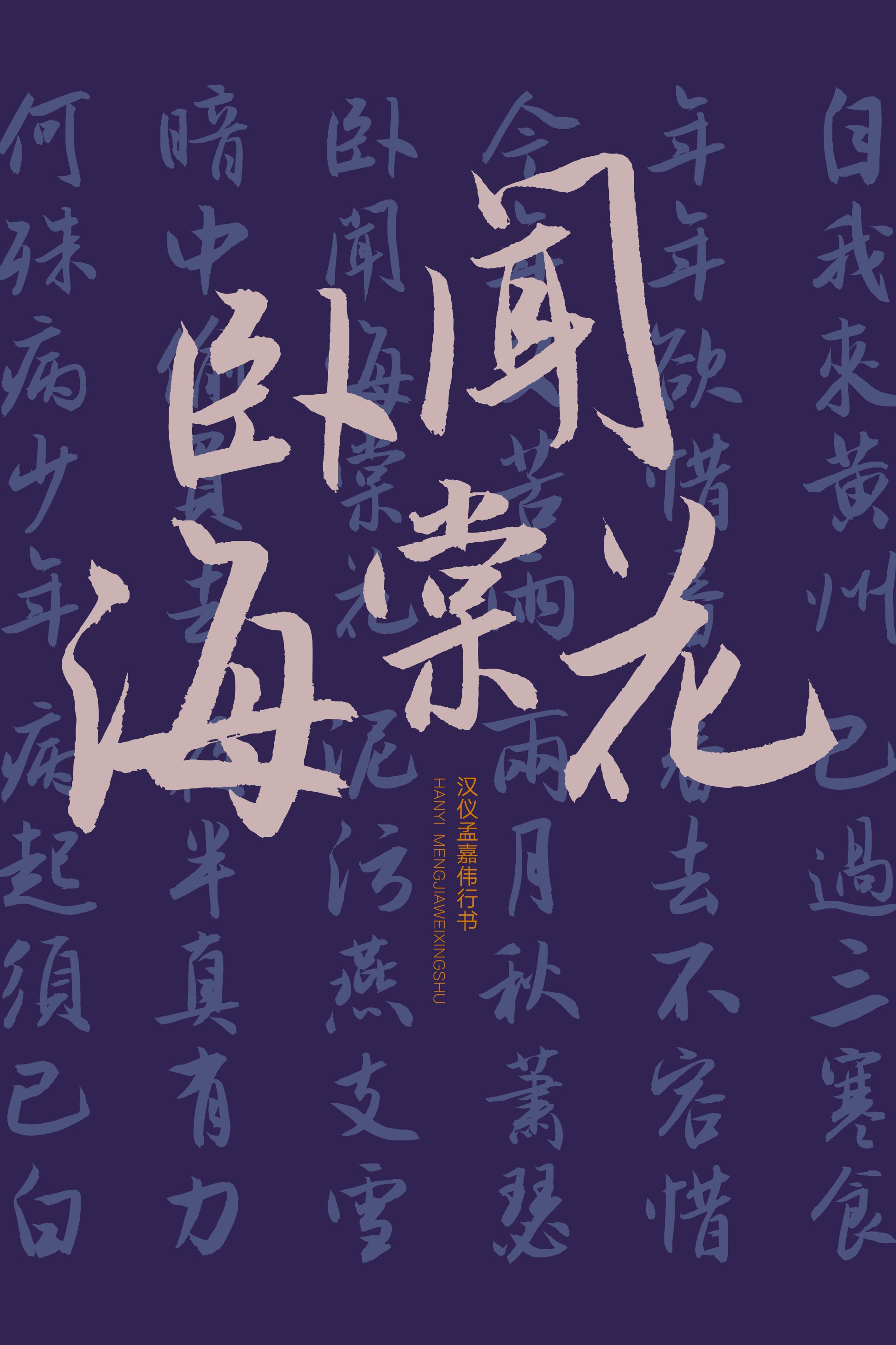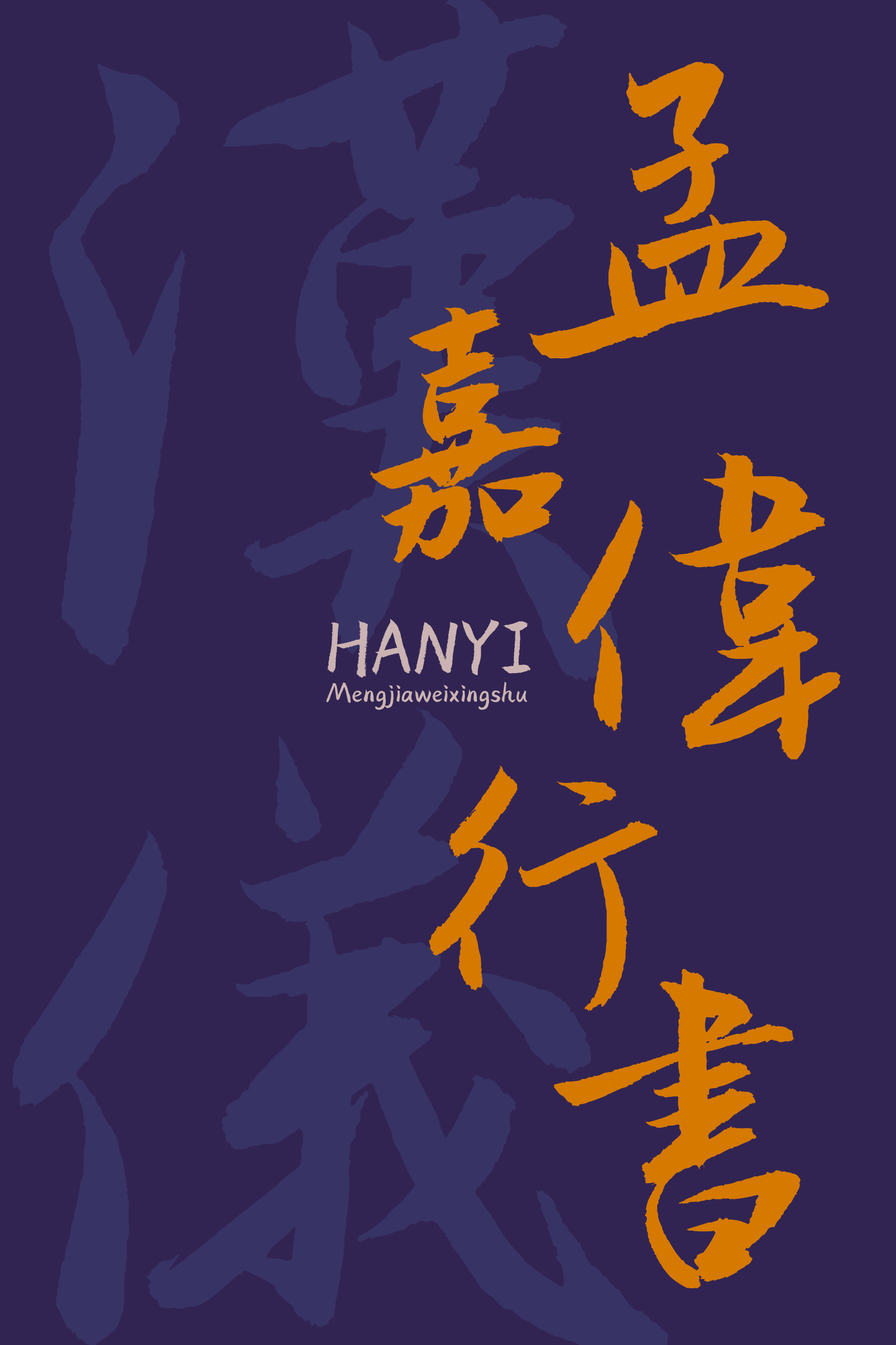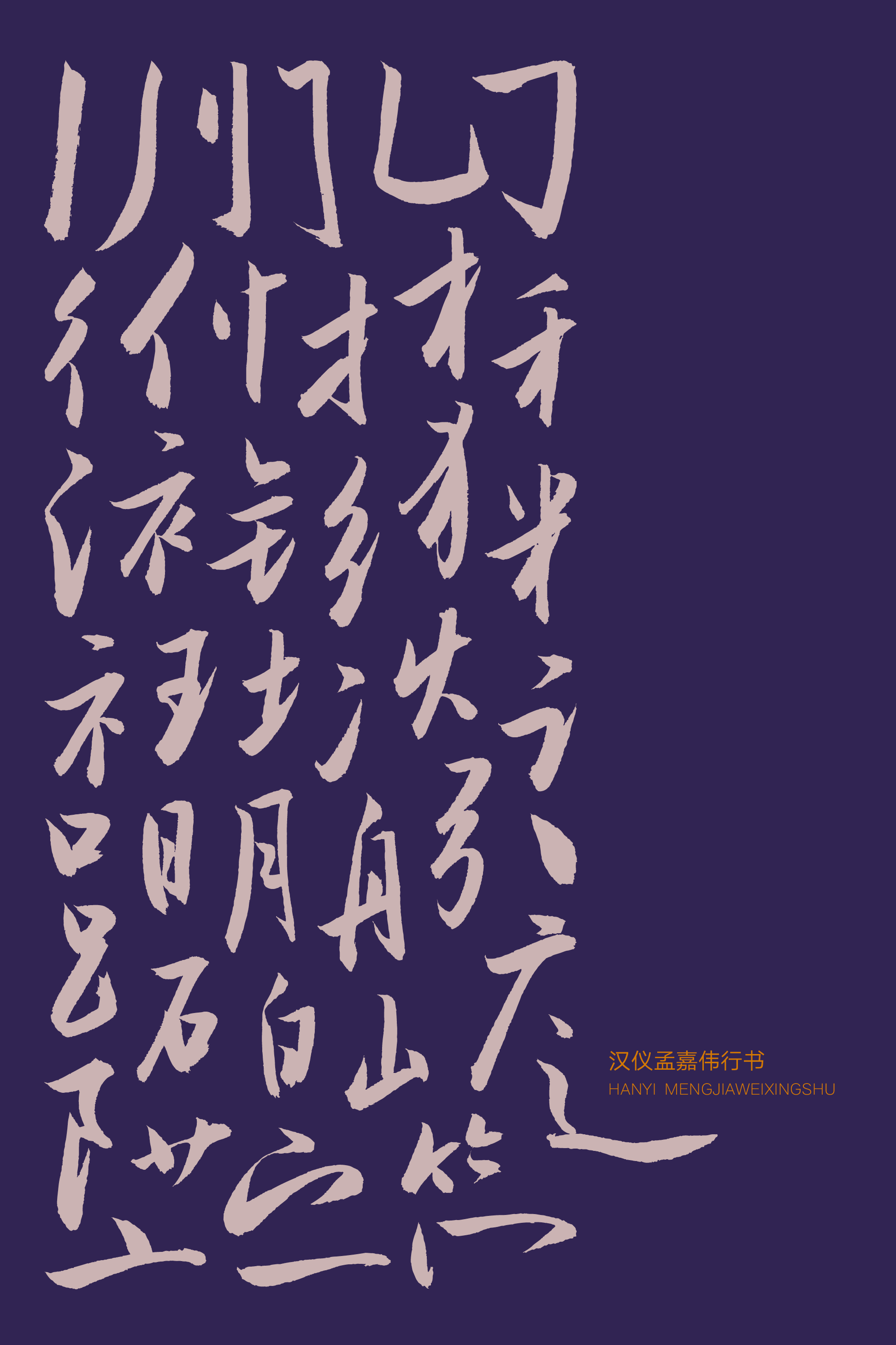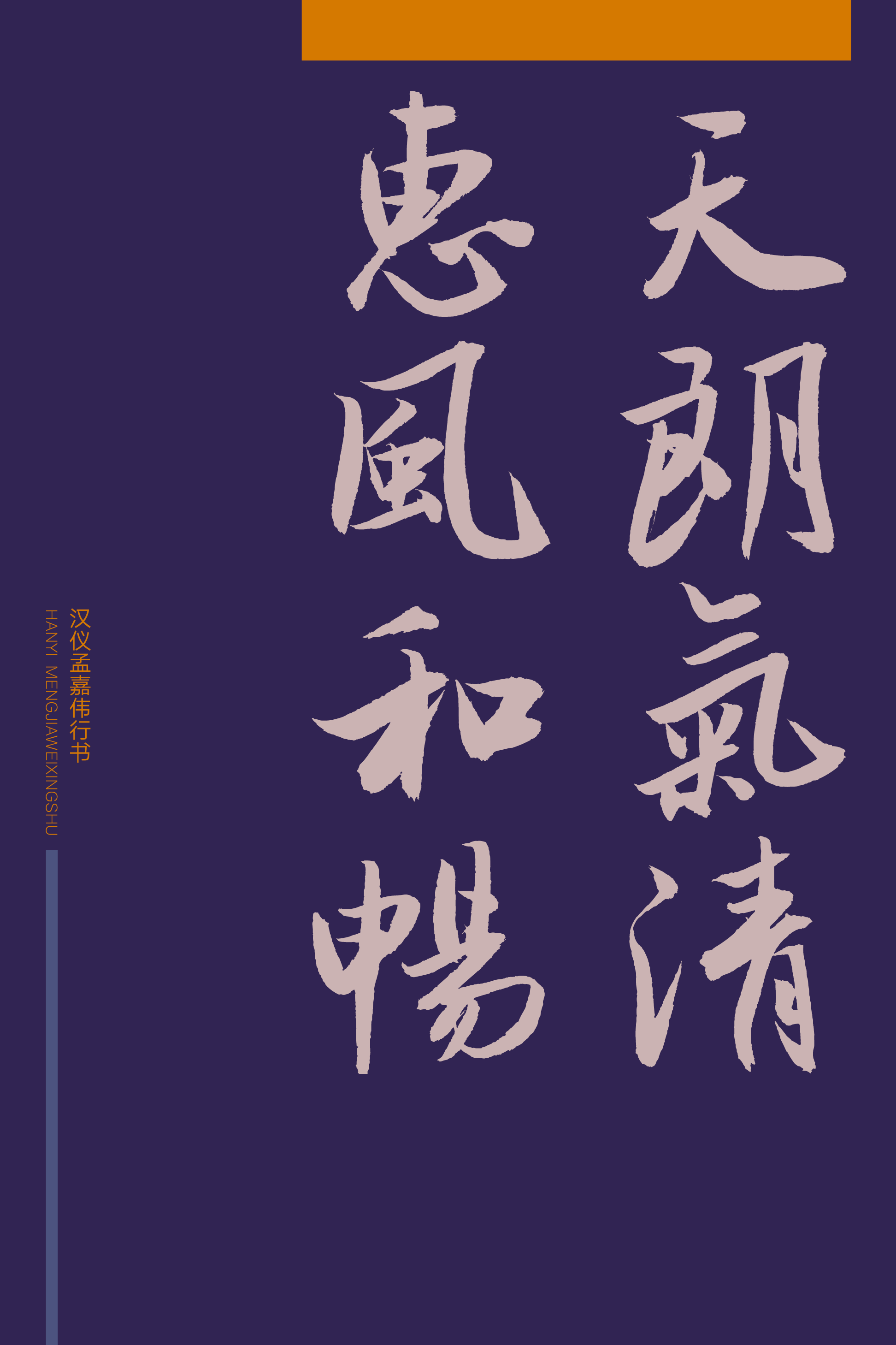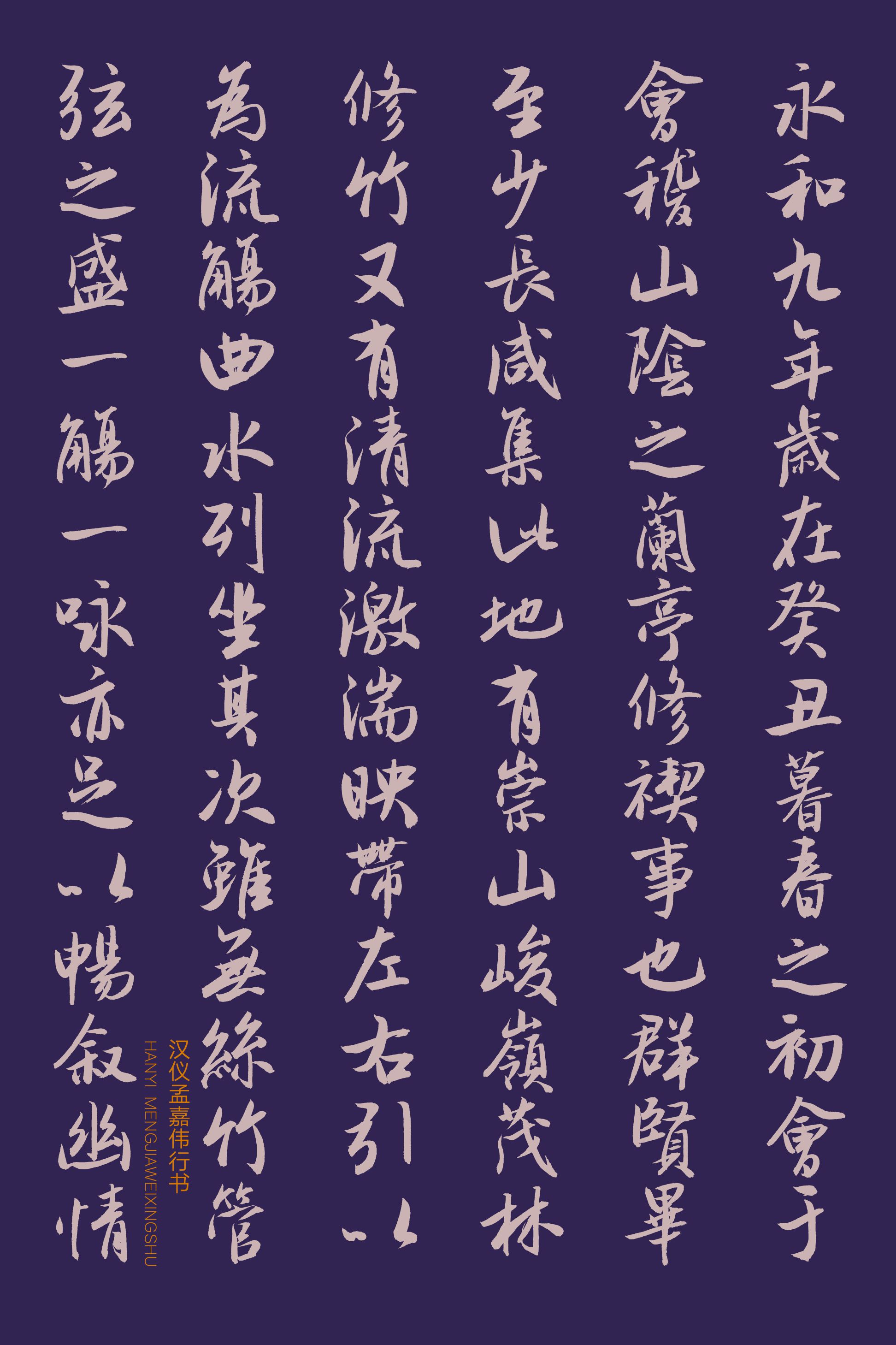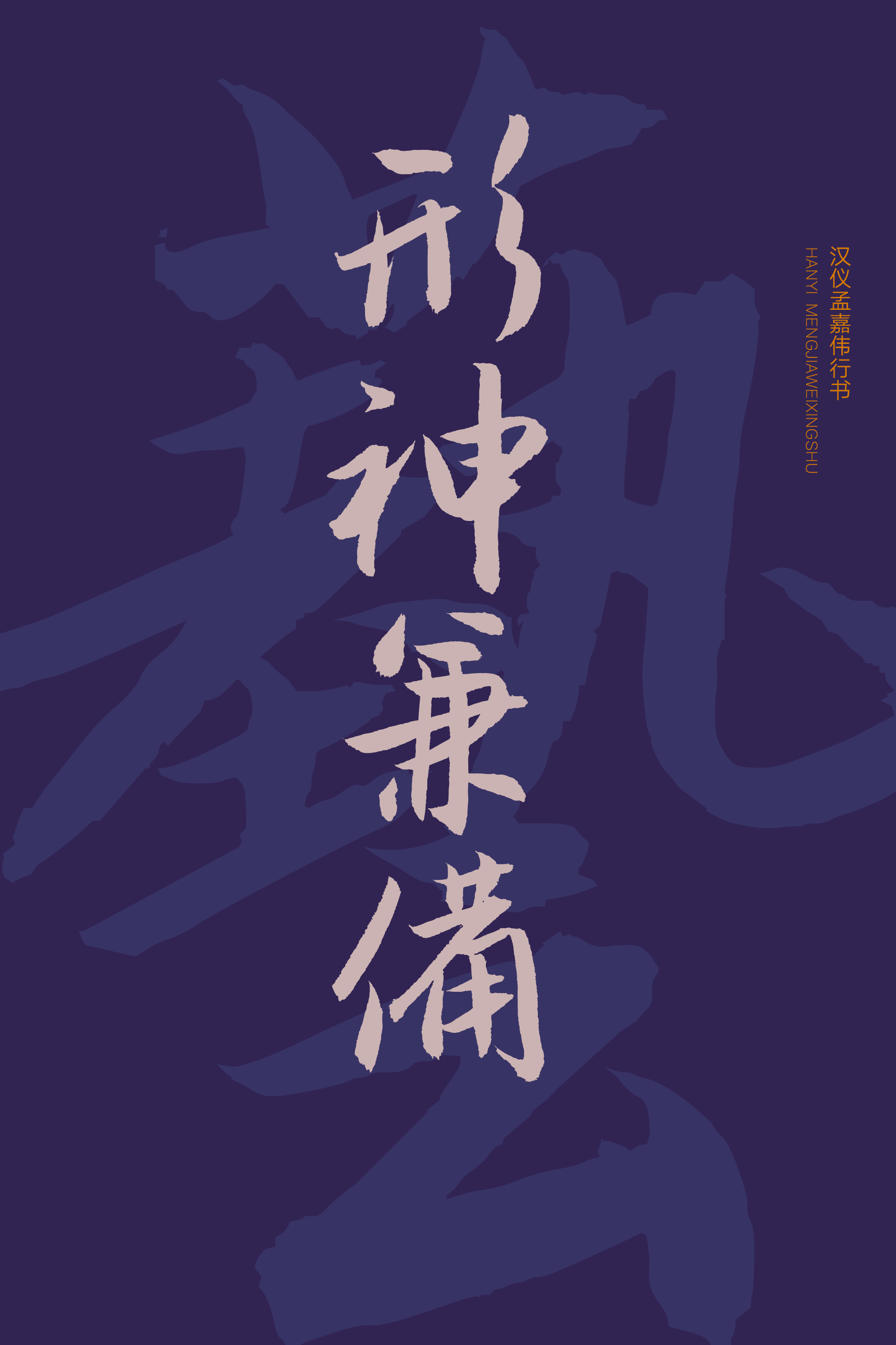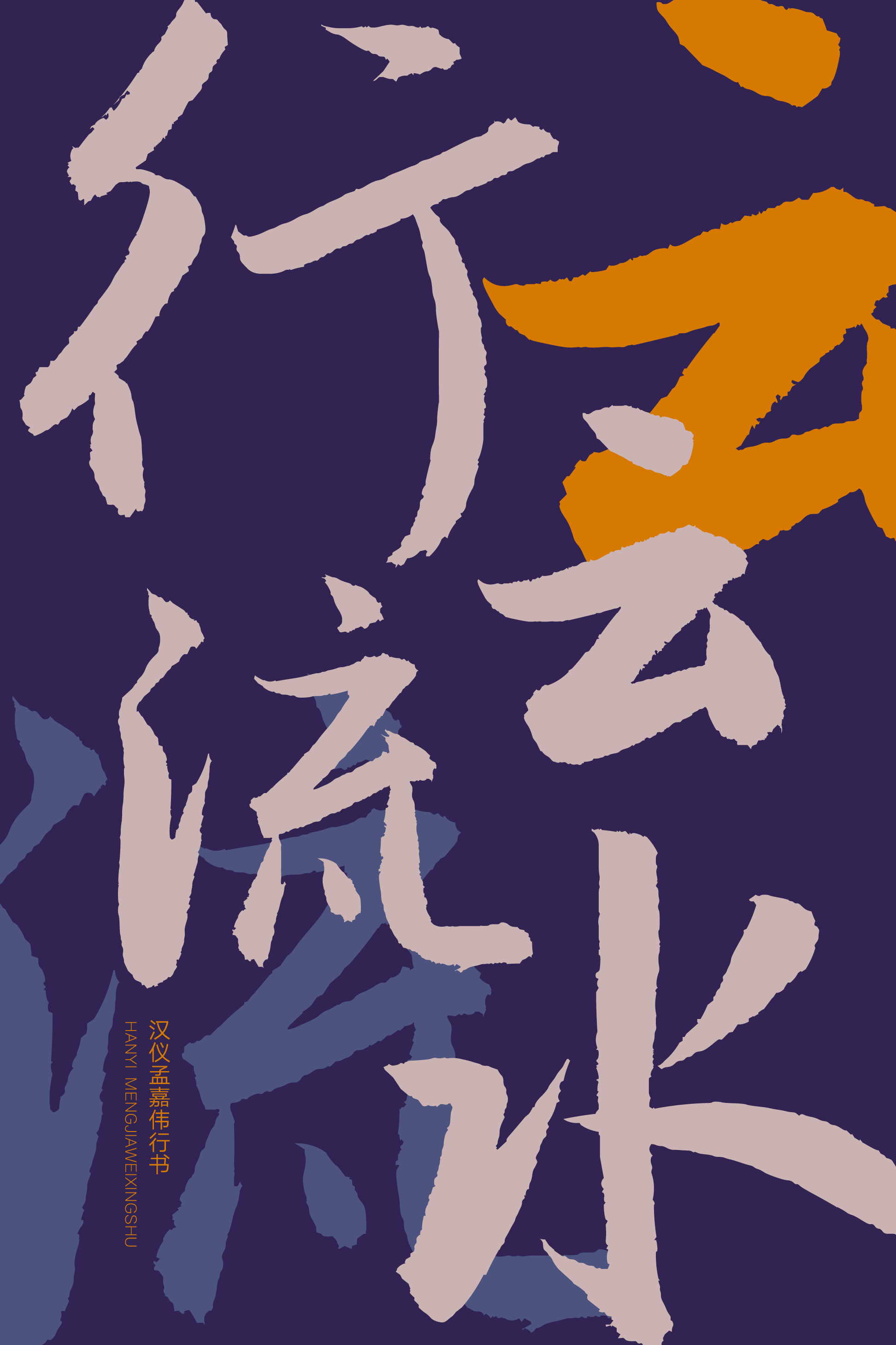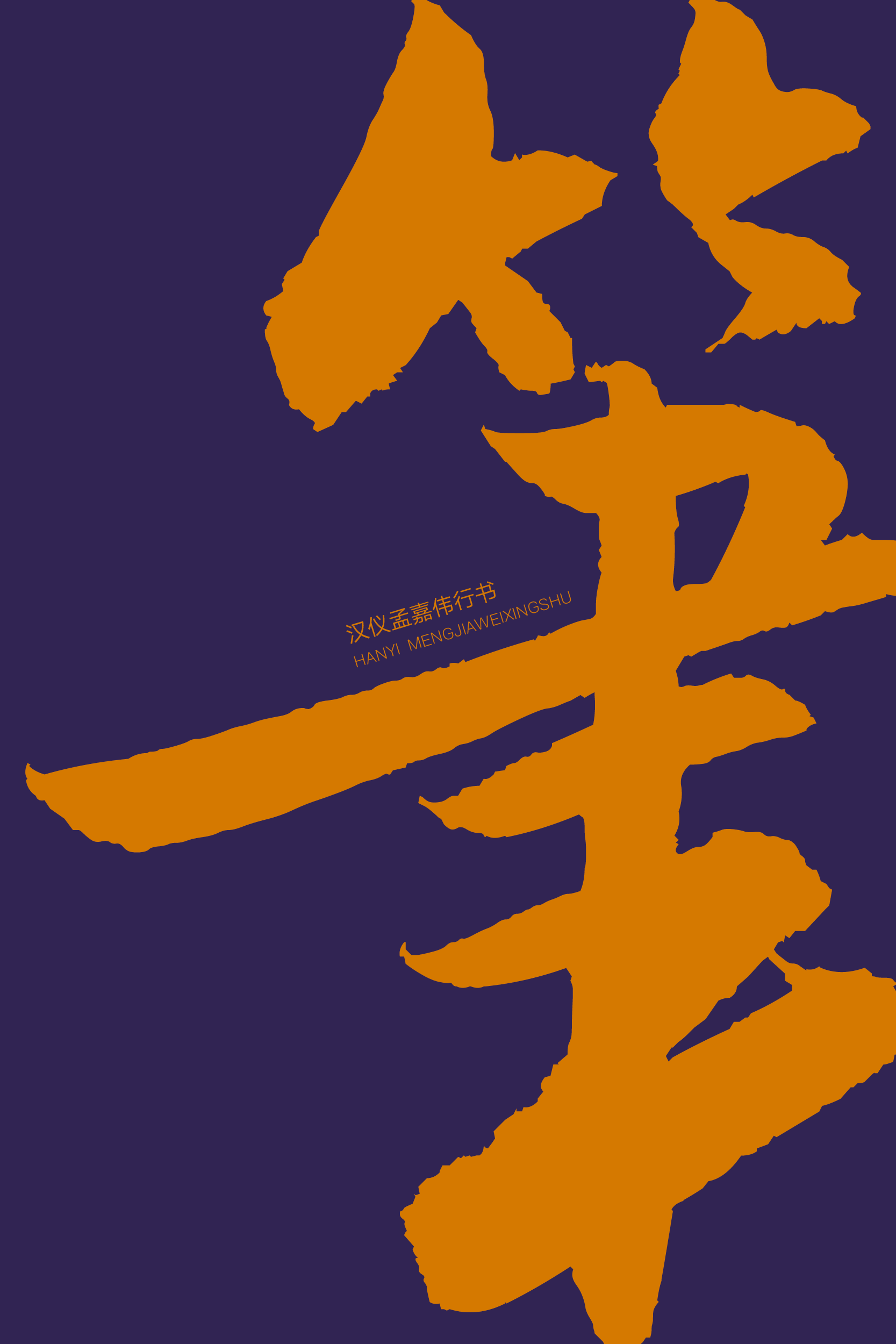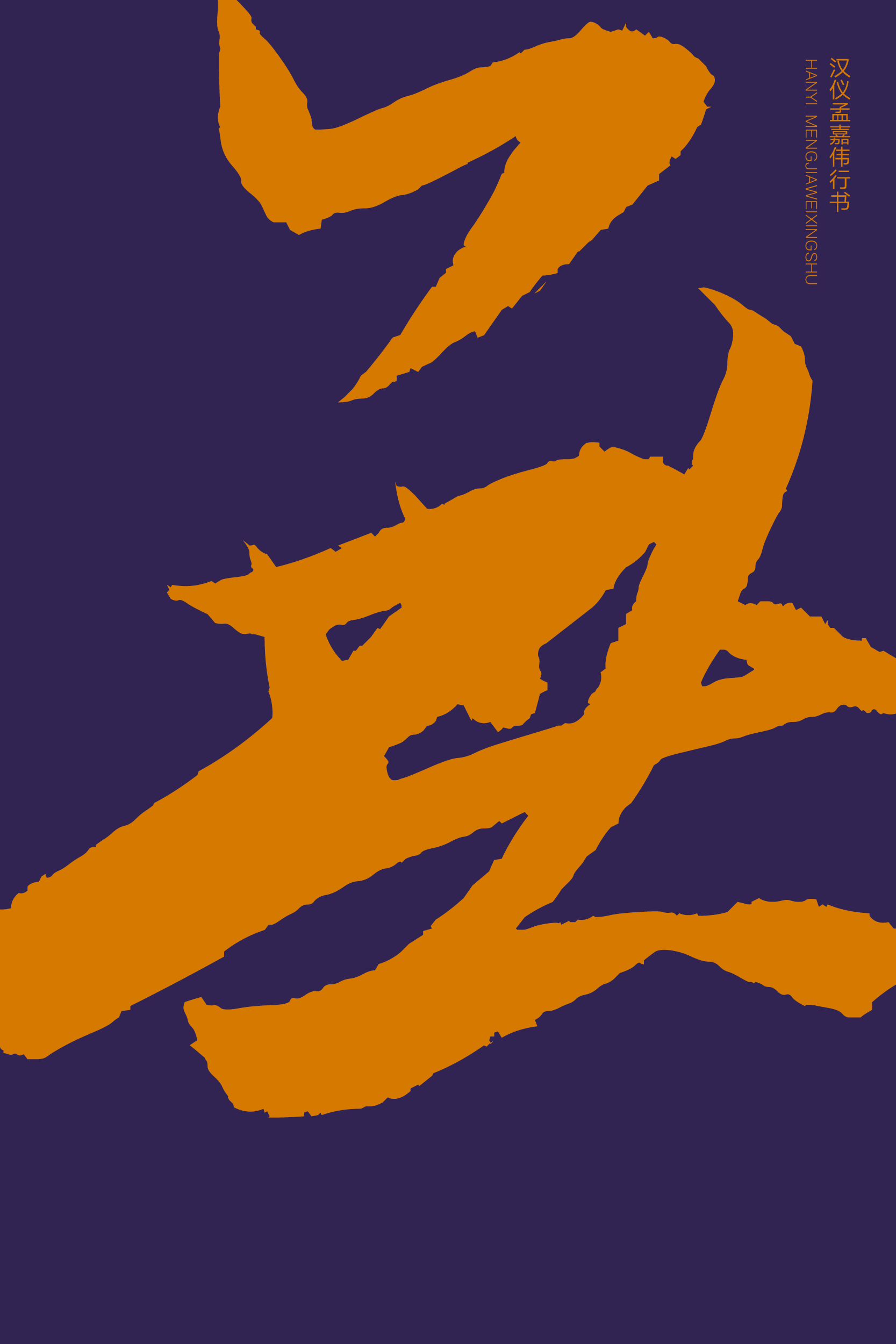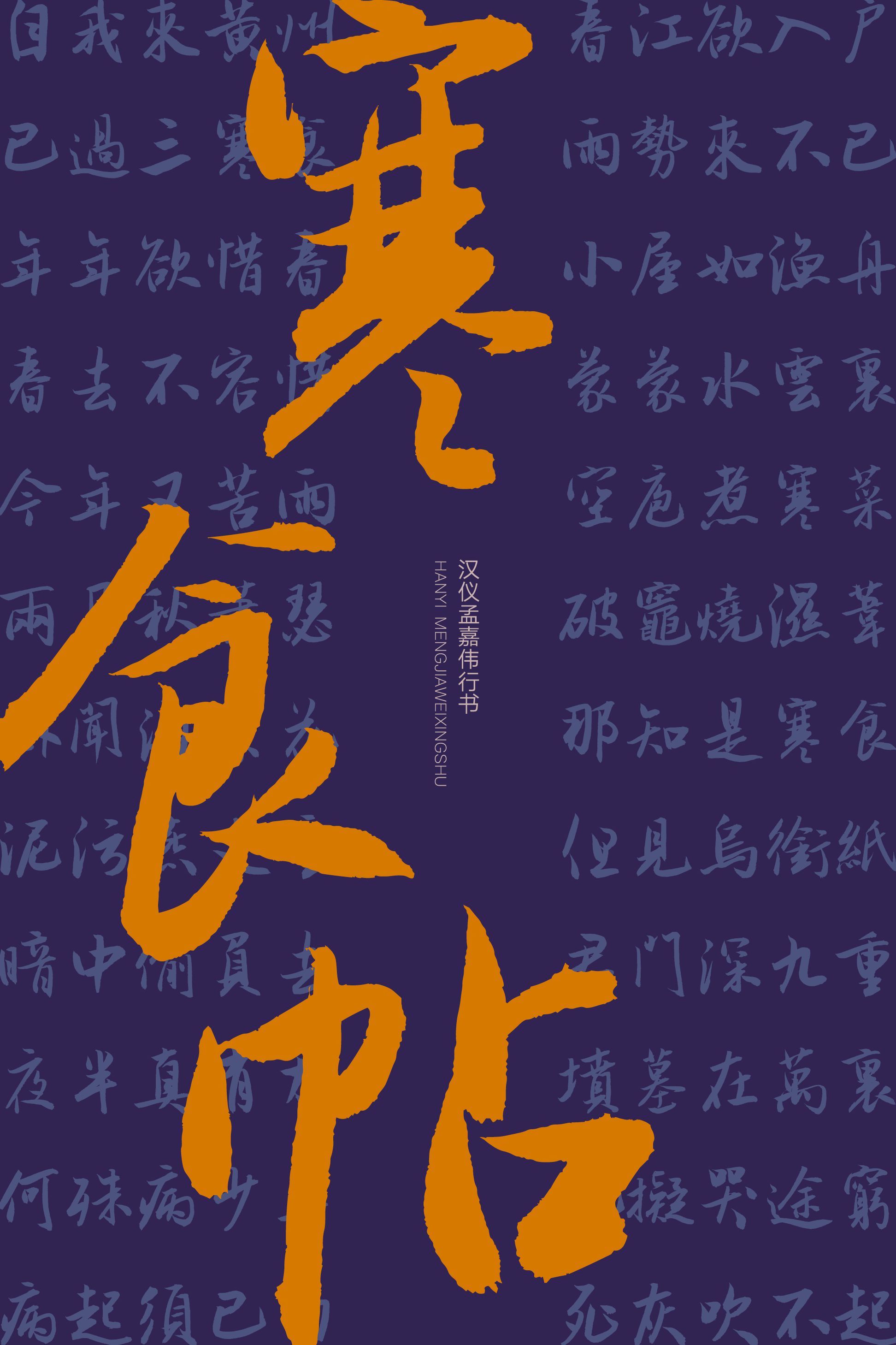
潇洒俊逸,行云流水的行书
汉仪孟嘉伟行书,由汉仪字库签约作者孟嘉伟书写,吸收二王、米芾的行书特征,潇洒俊逸,清劲而行,终成独特的行书书写风格。这款字体笔法行云流水、苍润朴秀,结体大开大合、收放自如,与艺术展览、书籍杂志、影视广告等使用场景颇为相称。
字形清俊而高挑。
体势略微倾斜。
笔墨流转于轻重缓急之间。
集字来源于二王、米芾,更添行书韵味。